市面上关于Apple Watch的各种评价仍在继续,不过透过一个小小的设计元素,我们也许能瞥见库比蒂诺的那些家伙在UI方面的新策略:开发新字体。
虽然苹果有过开发字体的历史,不过近20年来,他们主要依赖的还是Helvetica系,即使在新的iPhone及桌面系统中也是如此。但Apple Watch却带来了一套由苹果自己全新开发的、尚未知名的无衬线字体;正如官网中所讲:“我们甚至专门开发了一种更易阅读的新字体。”
那么,苹果为什么突然间又开始自己开发字体了?字体设计师兼字体授权公司FontShop的创始人Erik Spiekermann认为,“他们不这样做才怪”。首先,对苹果来说,创建新字体远比购买授权要划算的多。“即使每台设备只需付一美分的授权费,对于那么大的数量级来说也是一笔可观的开销,这足够你好好设计开发一款自己的字体了。”
此外,要为一款特定的设备寻找一套最适合的字体,这也许是更加困难的事情。毕竟,市面上没有哪款字体是专门为你的设备量身定制的。过去,苹果一直宣称由于良好的易读性而采用Helvetica,但这个解释未必站得住脚。Helvetica的著名之处在于它那中世纪现代风格的味道;它并不是为如今的小屏幕设备而设计的。Spiekermann更是认为,对于苹果在移动设备中所设置的字号来说,Helvetica几乎是体现不出什么价值的。
而Apple Watch字体(姑且这么叫)生来就只针对于一件事:让文字在如此微小的屏幕上更加易读。它的设计在很大程度上借鉴了DIN系,这是一种在易读性和空间利用率方面都很不错的字体。魏玛时期的德国将该字体用在公路与铁路的指示牌上,而后人则向其字形中增加了更多的弧形,以更加适应数码设备的特性。略具讽刺意味的是,Apple Watch字体和安卓自带的Roboto也很相似。“看来他们两家的团队都在寻找具有某种特性的字体风格,并且殊途同归了”Typographica的Stephen Coles这样说。
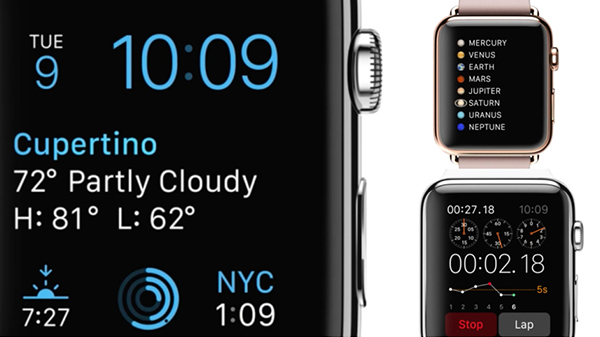
苹果自己打造字体的另外一个因素也许在品牌方面。“这也是我对他们使用Helvetica字体的另一个质疑——它并不属于苹果的品牌体系,任何人都可以效仿。”Spiekermann说。自己定制开发的字体则不会有这方面的问题,虽然它不像苹果自己的另外一款字体Chicago那样的特色鲜明。
我们有理由听听Spiekermann谈论苹果字体方面的话题——因为苹果本身就在听。Spiekermann与Jony Ive熟识已久,并且时不时的接到苹果打来的征询字体使用建议的电话。他还在今年7月收到了苹果的offer,推测是去带一个新的字体设计团队。不过Spiekermann拒掉了这份offer(“我不想让自己的退休生活被工作毁掉”,他这样解释)。他说苹果确实在打造自家字体这件事上变得认真起来,为了向所有的用户传递更出色的产品体验。